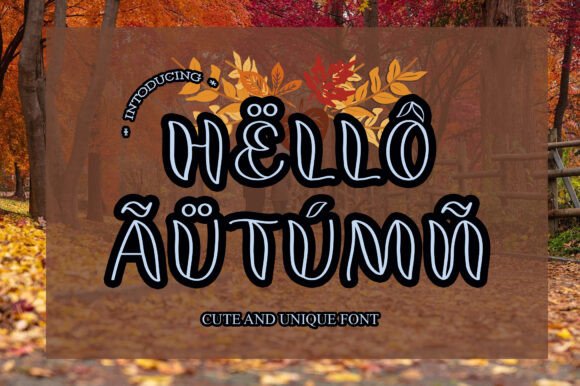
Hello Autumn
Hello Autumnのような高品質の素材をお探しの場合、このプレミアムパッケージはクリエイティブなプロジェクトに素晴らしい選択です。
POD(オンデマンド印刷)製品、結婚式の招待状、またはソーシャルメディアのグラフィックを作成している場合でも、Hello Autumnは理想的です。